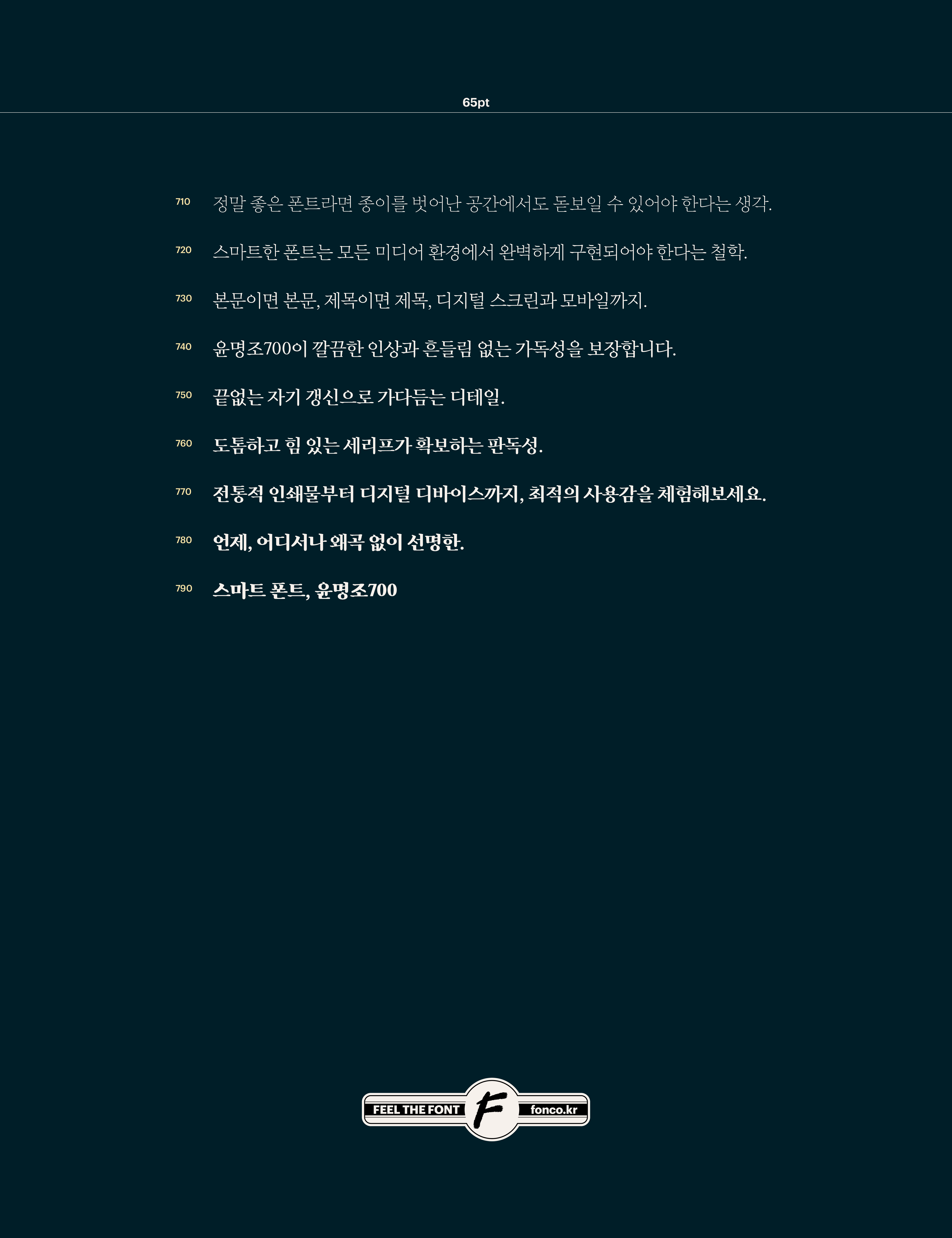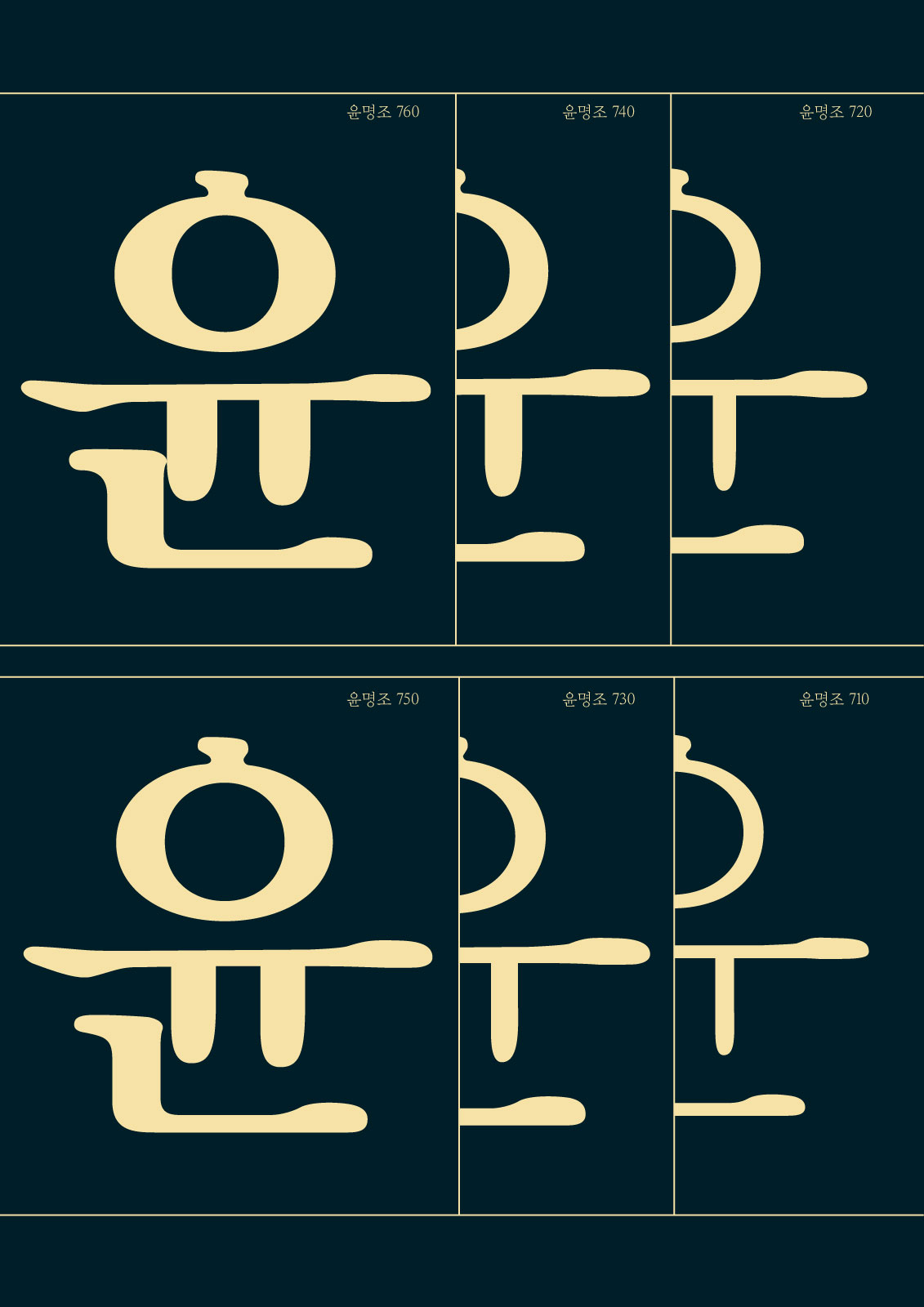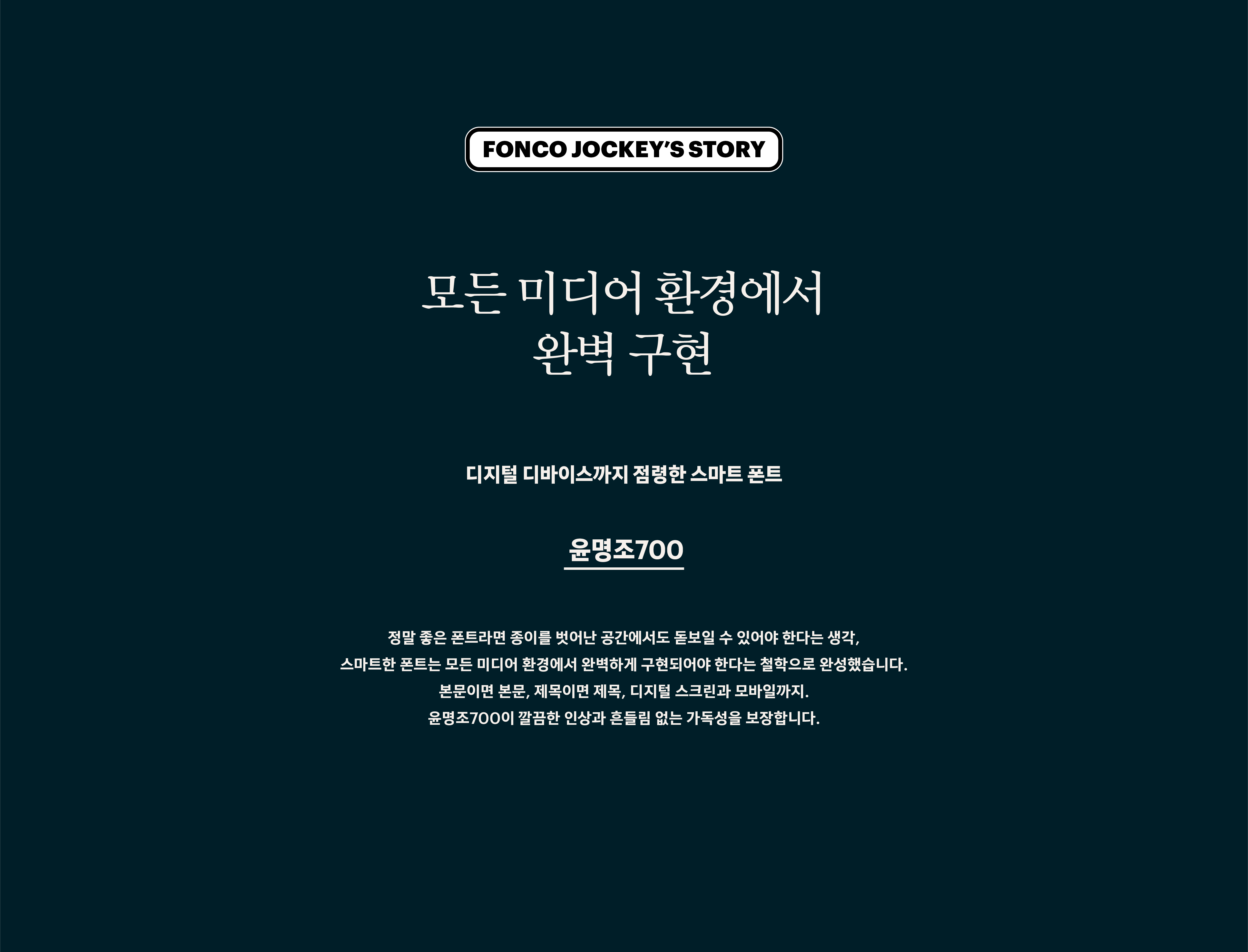
윤명조700
Yoon 윤명조700
정말 좋은 폰트라면 종이를 벗어난 공간에서도 돋보일 수 있어야 한다는 생각, 스마트한 폰트는 모든 미디어 환경에서 완벽하게 구현되어야 한다는 철학으로 완성했습니다. 본문이면 본문, 제목이면 제목, 디지털 스크린과 모바일까지. 윤명조700이 깔끔한 인상과 흔들림 없는 가독성을 보장합니다.